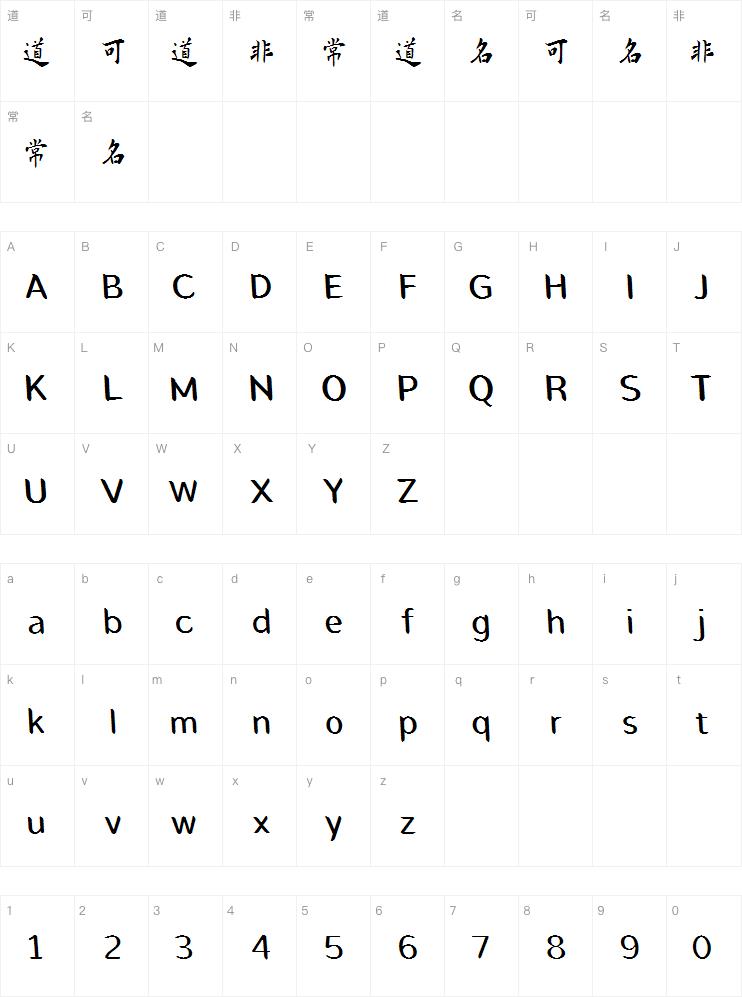
大萌兰花楷是一款清雅国风+软萌治愈的创新楷书艺术字体。设计以传统楷书为骨架,以幽兰风韵为意境,融合圆润可爱的萌系笔触,打破传统楷书的严肃刻板,兼顾书法的端正雅致与现代审美的温柔灵动。整体定位“字含兰香、笔藏萌趣、形守楷骨”,适配国风文创、文案排版、手账海报、国风视觉设计等多元场景,打造兼具古典诗意与年轻化质感的国风字体。